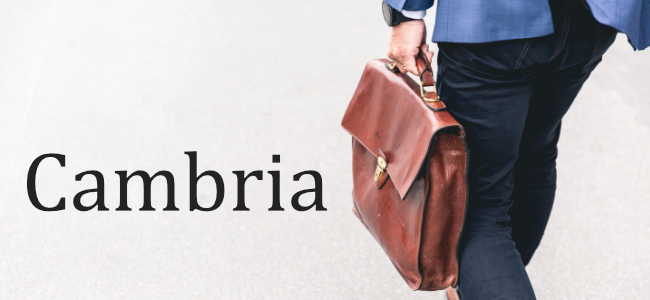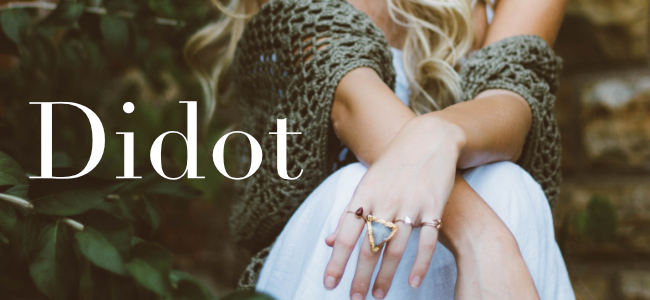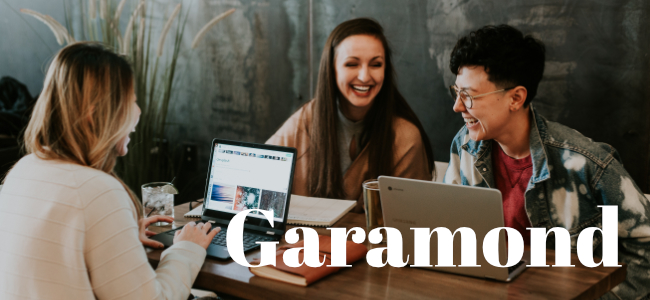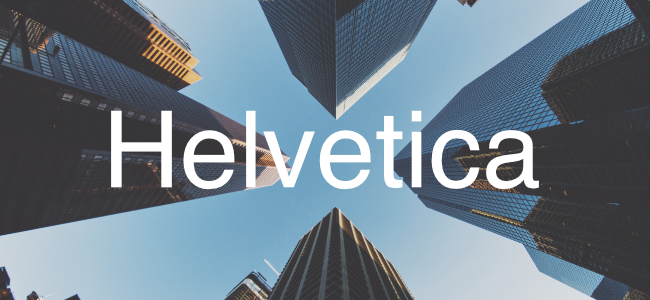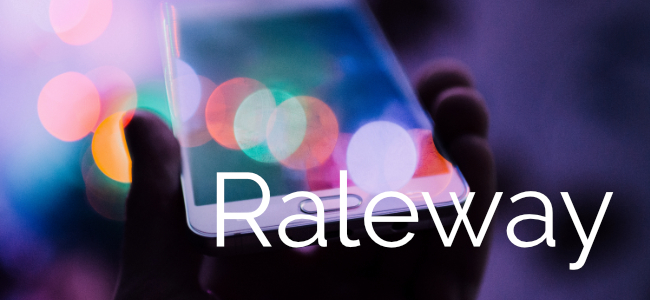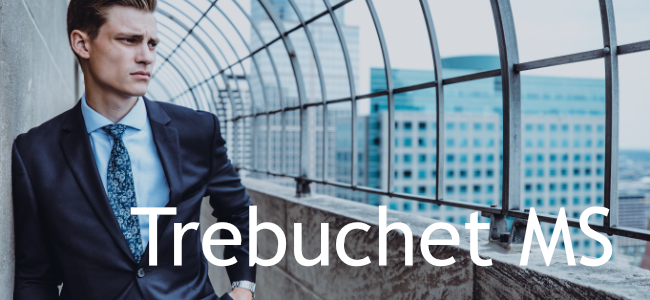
Lors d’une recherche d’emploi, le curriculum vitae (CV) est un élément essentiel qu’un candidat ne doit négliger sous aucun prétexte.
Afin d’optimiser ses chances d’être recruté, il doit veiller à tous les détails et en particulier à la typographie utilisée.
Celle-ci doit être aisément lisible car un CV difficile à lire termine généralement dans la poubelle du recruteur. De même, elle peut, si vous candidatez pour un poste où la créativité est primordiale, apporter une touche d’originalité à votre CV.
Pour vous aider à faire le bon choix, voici 7 typographies gratuites parfaitement adaptées à la conception d’un CV.
Voilà une typographie qui a réussi à s’imposer comme une référence pour la rédaction de documents comme un CV. Il faut dire qu’elle est une police légère, facile à lire et plutôt élégante même lorsqu’elle est imprimée en petite taille.
Très classique, elle manque un peu d’originalité si bien qu’elle est déconseillée si vous postulez à un poste de créatif.
Il s’agit d’une valeur sûre en matière de typographie pour un CV. Imaginée à l’époque de la Révolution Française – elle porte le nom de son inventeur Firmin Didot -, cette police a une vraie dimension créative bien qu’elle soit souvent classée comme “classique”.
Utilisée par petites touches dans un CV, cette police apportera du dynamisme et un brin d’originalité. Ce n’est pas pour rien qu’elle est très appréciée dans l’univers de la mode…
Pour un CV sobre et professionnel, la typographie Helvetica est idéale. Très populaire dans le monde du travail, cette police brille par sa légèreté et sa “propreté”.
Très facile à lire quelle que soit la taille d’impression, elle vous garantit un CV élégant qui renverra une image de professionnalisme. En revanche, popularité oblige, elle ne vous aidera pas nécessairement à vous démarquer de vos concurrents.
Voilà une police qui diffère quelque peu de celles que nous avons présentées jusque-là. Si la typographie Trebuchet MS renvoie une image professionnelle, elle doit effectivement permettre de vous démarquer des autres candidats.
Avec son apparence moderne et texturée et sa grande lisibilité, cette police dispose de réels atouts pour vous aider à faire la différence.
À l’heure où l’utilisation de la trop classique police “Times New Roman” est de plus en plus perçue comme un manque de motivation de la part du candidat, avoir recours à la typographie Garamond apparaît comme une excellente alternative.
Extrêmement simple à lire et ayant fait l’objet de diverses modernisations, cette police est très appréciée des publicitaires qui l’utilisent pour leurs campagnes de communication.
Sur un CV, cette police devrait vous aider à orienter les yeux du recruteur vers vos points forts. À vous donc de l’utiliser à bon escient…
Aérienne, élégante et féminine, la police Raleway est souvent considérée comme “haut de gamme”. Il faut dire qu’elle est professionnelle mais peut apporter un brin de fantaisie à votre CV si vous la préférez à une police plus “traditionnelle”.
Si elle ne plaît pas nécessairement à tous les recruteurs, elle est généralement très appréciée dans les secteurs d’activité que sont la mode et le digital.
Si malgré nos conseils vous hésitez encore, sachez qu’il existe une petite astuce pour être sûr de prendre la bonne décision : optez pour la police qu’utilise l’entreprise pour laquelle vous candidatez dans sa communication et en particulier ses communiqués de presse.